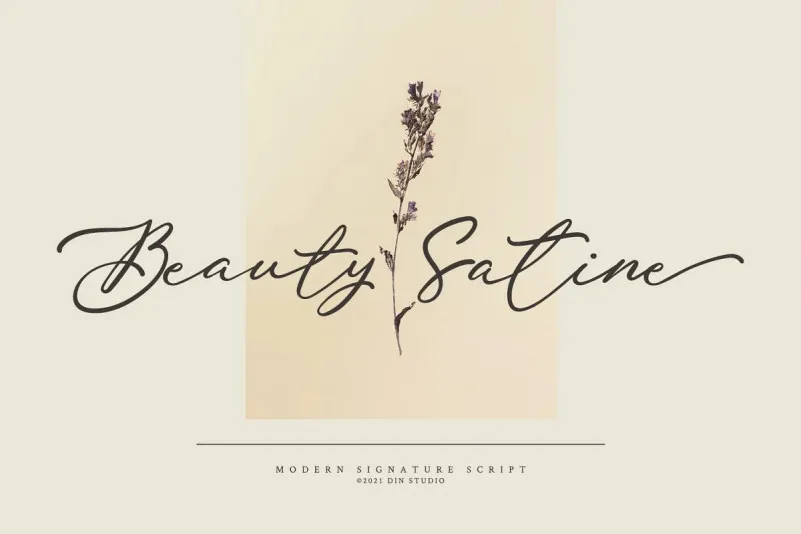
A Beauty Satine Font é uma excelente escolha para quem busca transitar entre a elegância moderna e a sofisticação do estilo calligráfico moderno. Esta tipografia script oferece um design limpo e arrojado, ideal para estilos de marca modernos e criativos. Com suas curvas perfeitas e linhas retas suaves, essa fonte não é apenas adequada como uma fonte assinatura; ela transmite a essência da elegância moderna. Seu design script limpo e sua textura rica dão um toque sofisticado e criativo às suas criações, tornando-a perfeita para aplicar em variados formatos de projetos, desde cabeçalhos até cartões de visita. O talentoso designer da 99designs soube capturar a essência do modernismo elegante, transformando essa fonte em uma ferramenta poderosa para quem deseja personalizar seus elementos digitais e offline. Use esta fonte para criar um impacto na sua identidade visual e tornar seu trabalho mais profissional. Com Beauty Satine Font, você pode explorar a sua criatividade com maior liberdade, seja através de logomarcas, cartões de visita ou até mesmo suas redes sociais. Este é um recurso que vai além da simples tipografia; ele transforma qualquer projeto digital no seu website em uma experiência visual única e memorável.